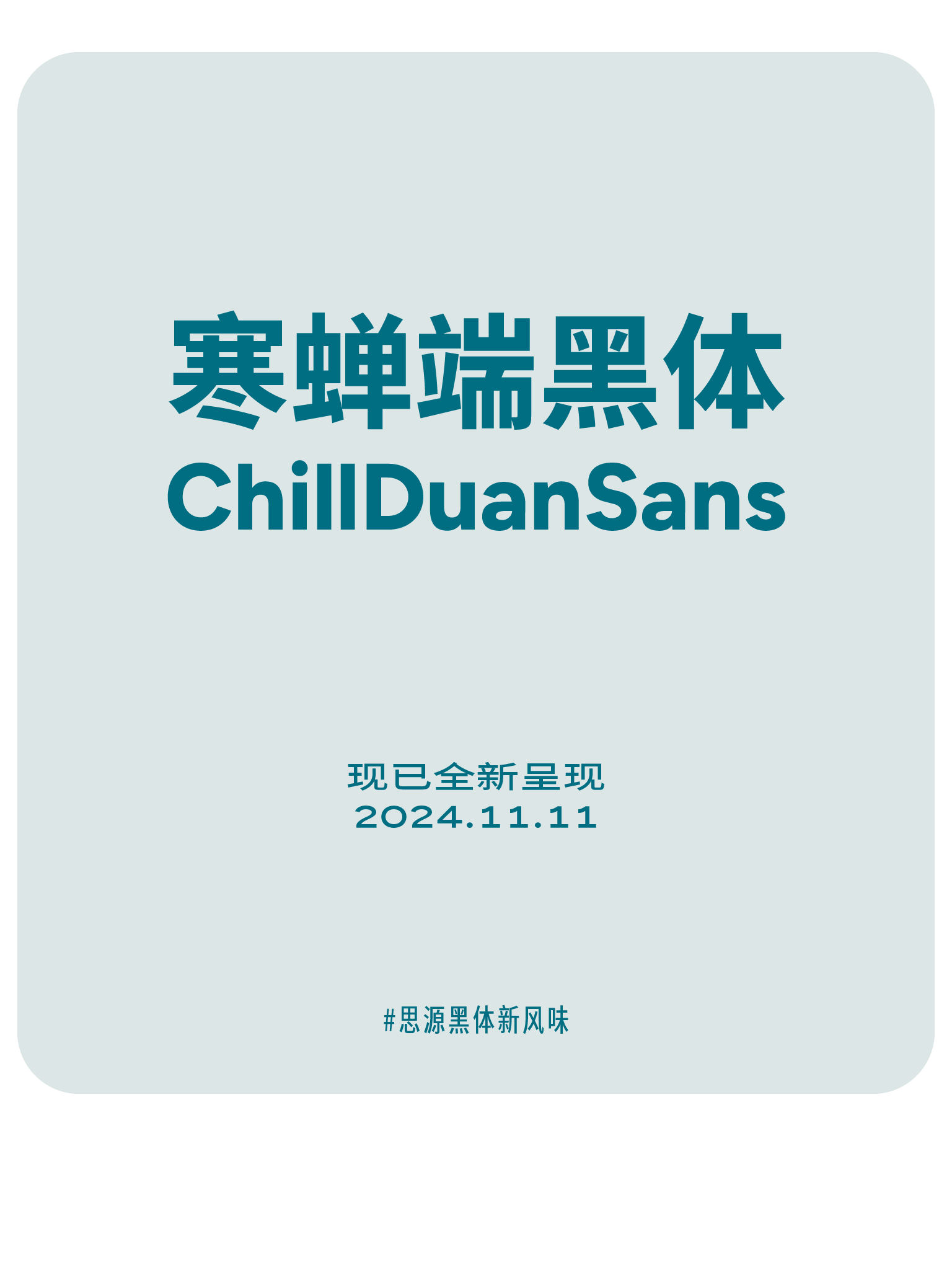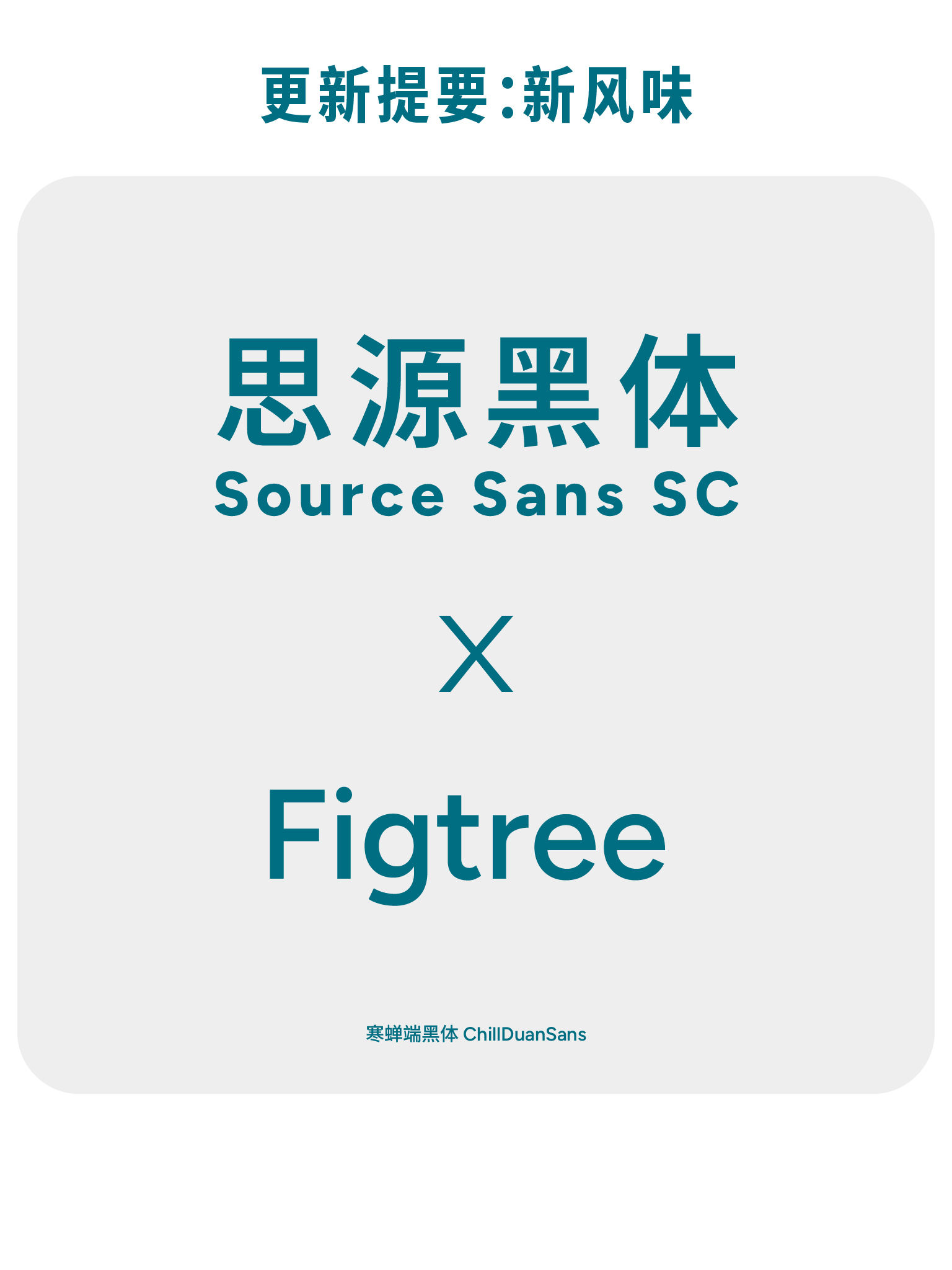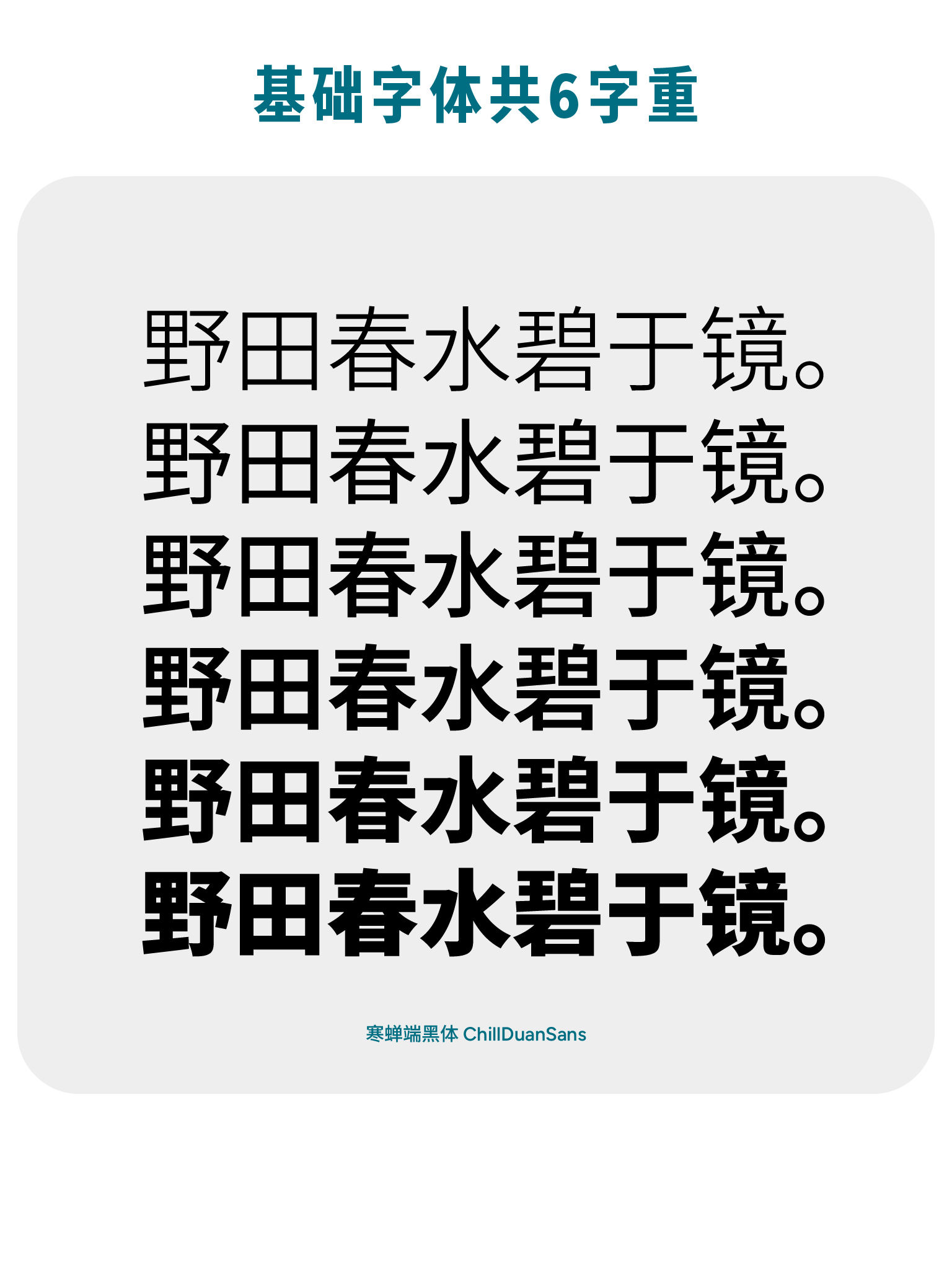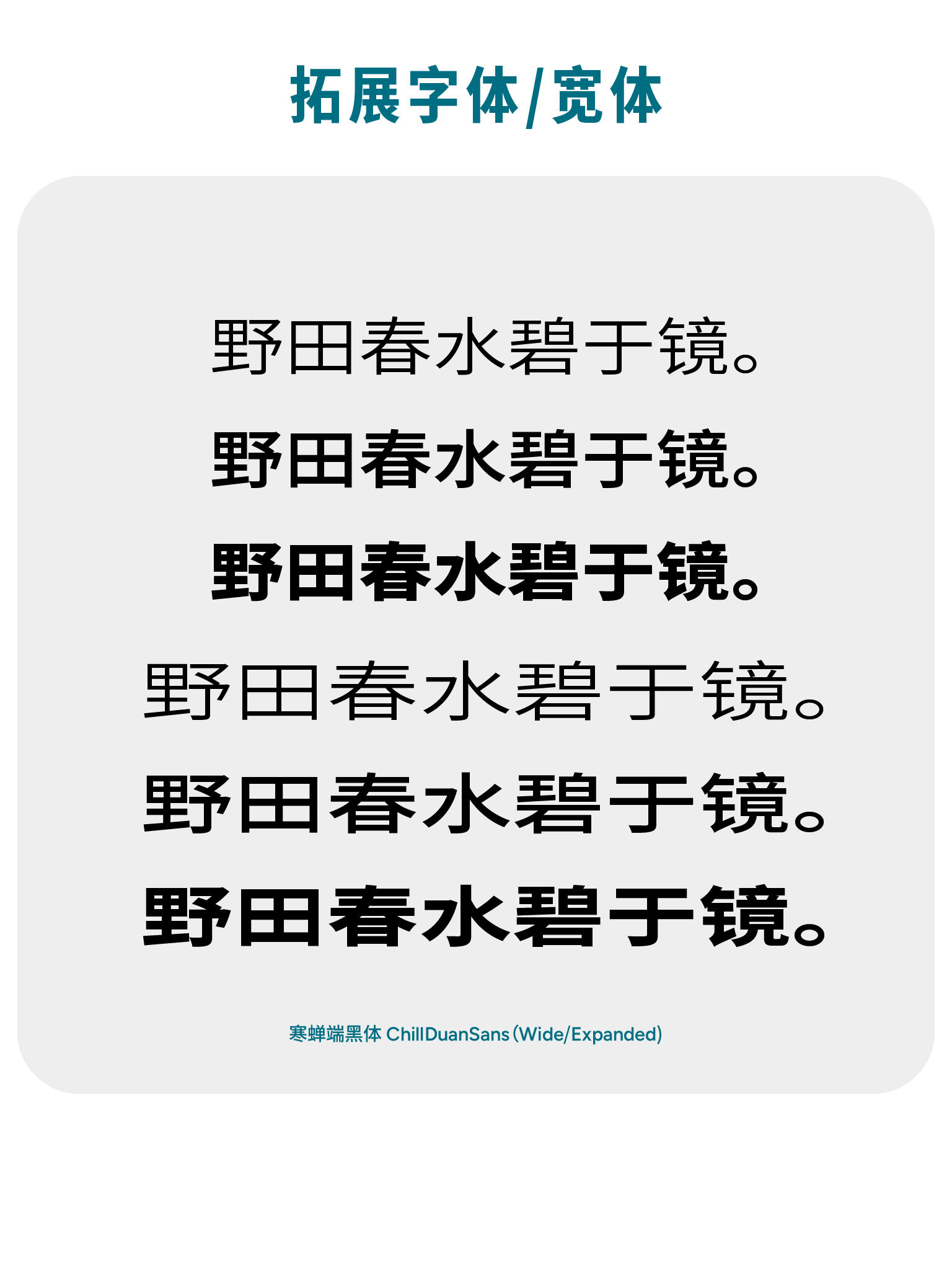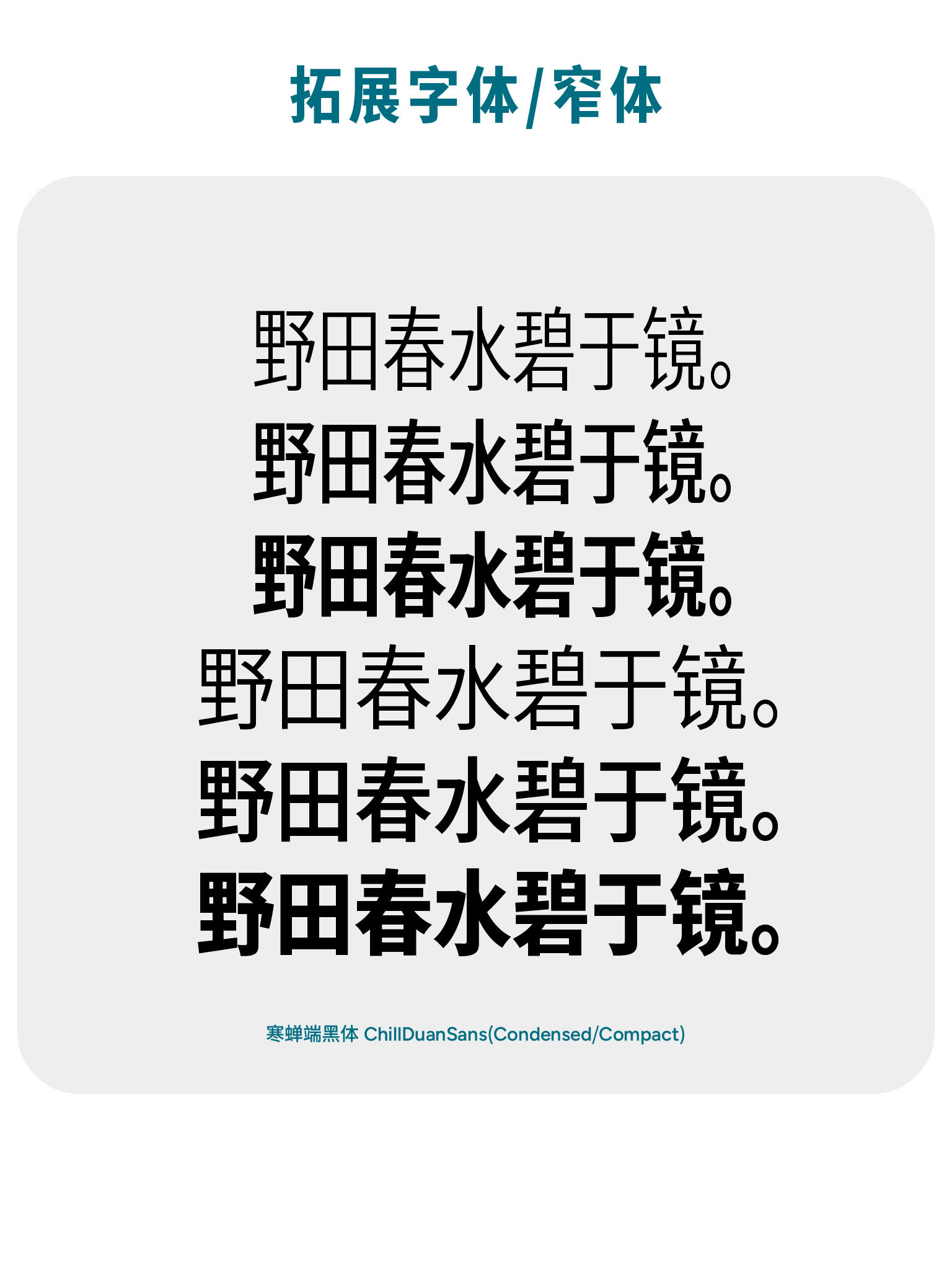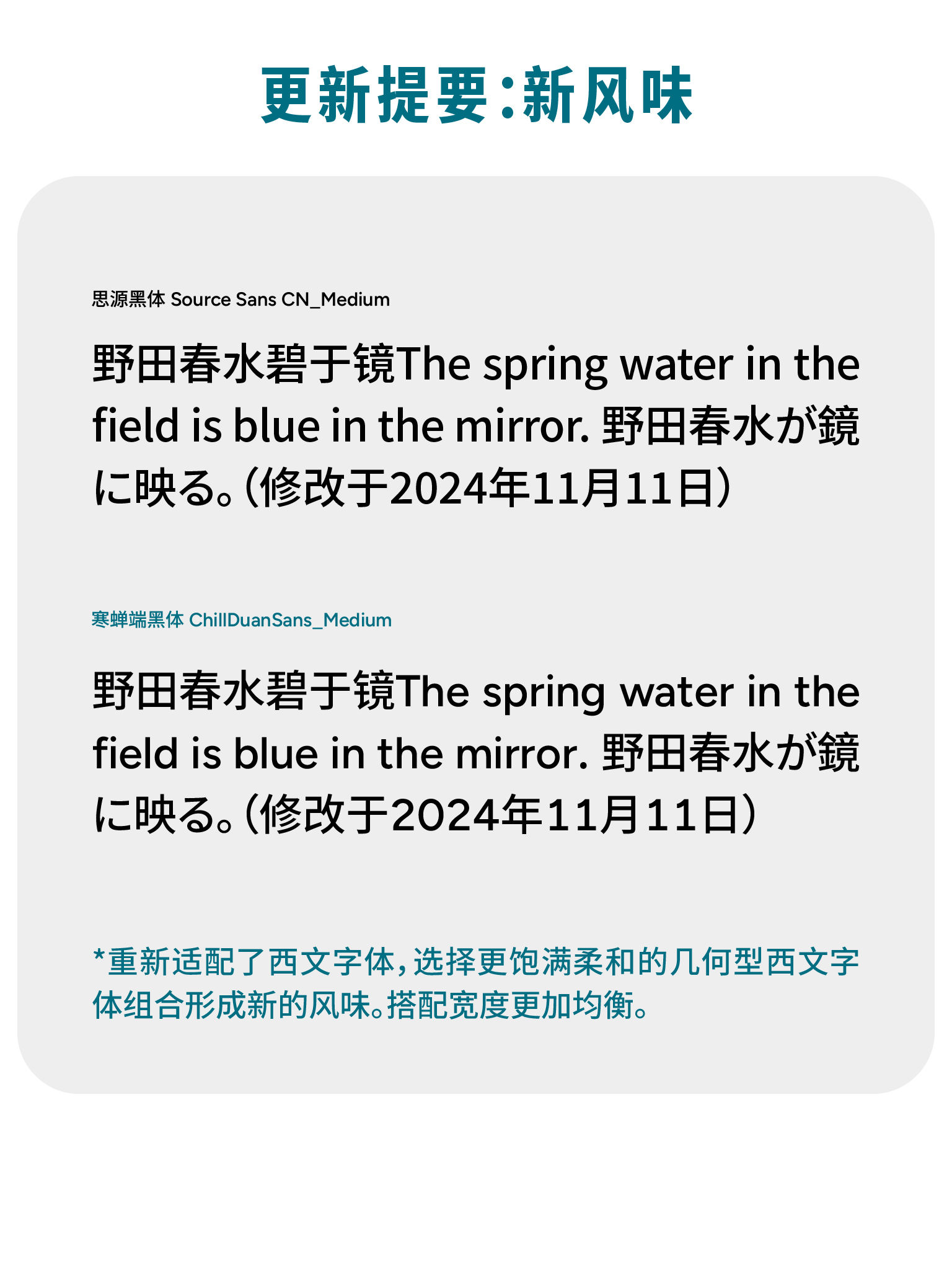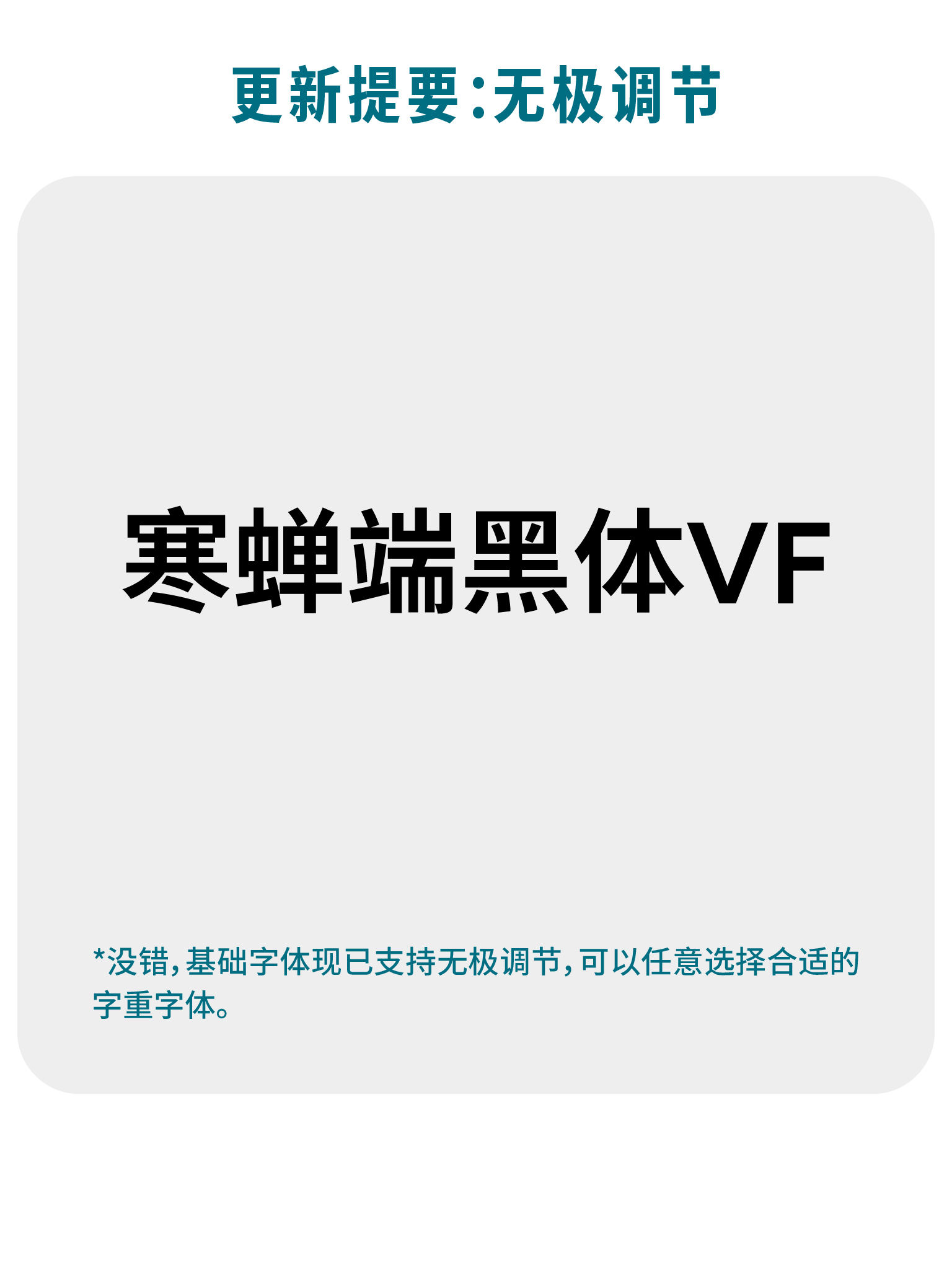
寒蝉端黑体是基于思源黑体的设计,特别提供了宽体与窄体两种变体版本。这两个版本通过重新插值技术生成,在保持原有字体设计精髓与风格统一的基础上,仅对字宽比例进行了针对性调整,未作其他结构性或字形上的改动。
这种设计主要是为了满足不同排版场景下的实际需求——宽体更适合需要视觉舒展、标题醒目的应用,而窄体则能在有限空间内实现更紧凑的排列,常用于正文或界面密集文字区域。为了便于使用者在不同字宽之间灵活切换与适配,我们也同步生成了与原版思源黑体插值参数对应的字体文件,确保整体排版协调性与兼容性。
寒蝉端黑体(ChillDuanSans)全新呈现预告,将于2024年11月11日发布,属于#思源黑体新风味系列
更新提要:新风味,思源黑体 Source Sans SC 搭配 Figtree,寒蝉端黑体 ChillDuanSans-刊刻Kntuk
寒蝉端黑体字体展示,共六种字重,使用示例文字“野田春水碧于镜。”演示从细到粗的不同粗细效果。
图片展示寒蝉端黑体 (ChillDuanSans) 的多种字重效果。
寒蝉端黑体(ChillDuanSans)字体样张,展示了“野田春水碧于镜”这句话在不同字重下的显示效果。
字体更新摘要,展示思源黑体和寒蝉端黑体的示例文字“野田春水碧于镜”,并注明修改日期。
更新提要:寒蝉端黑体VF支持无极调节,可任意选择字重。